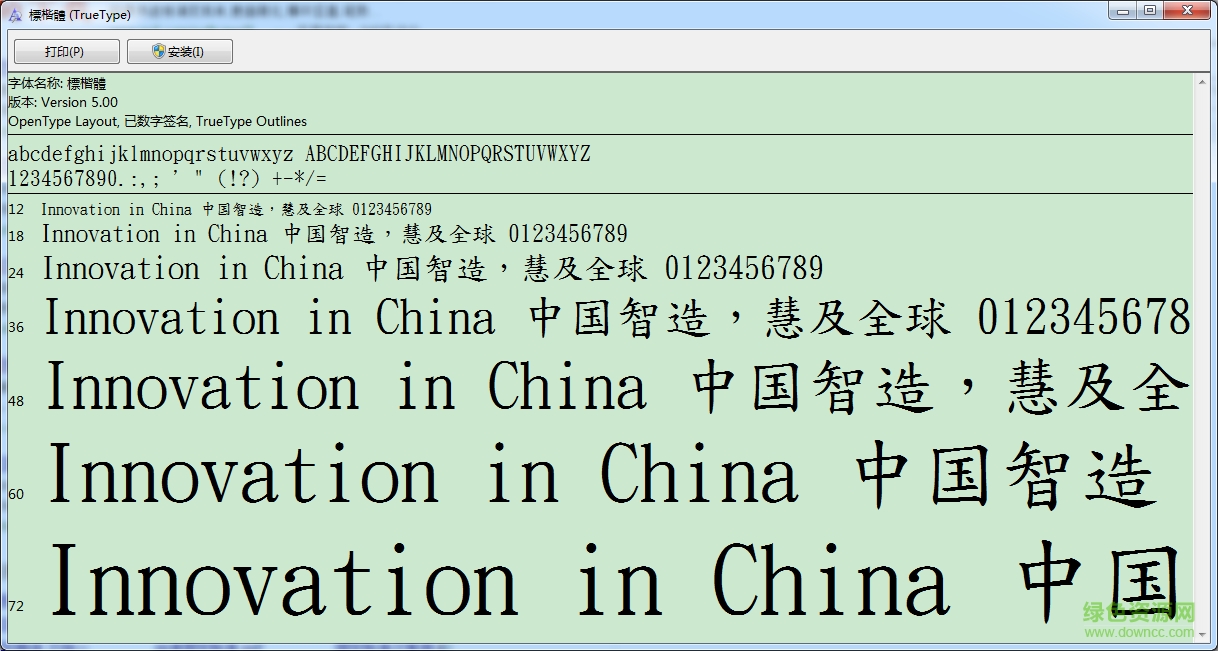
標(biāo)楷體繁體是微軟根據(jù)臺灣教育部的國字標(biāo)準(zhǔn)字體標(biāo)準(zhǔn)打造的一款中文輸入字體,形體方正,筆畫平直,非常的美觀,喜歡這款字體的朋友可以來綠色資源網(wǎng)下載使用!
標(biāo)楷體是微軟公司開發(fā)的TrueType中文字型。標(biāo)楷體字形的整理,是以傳統(tǒng)楷體為原型,并嚴(yán)格按照漢字的字源原則而制定的,其中區(qū)分了許多近世所混淆的字形構(gòu)件,強(qiáng)化了漢字的科學(xué)性,便于學(xué)習(xí)使用。